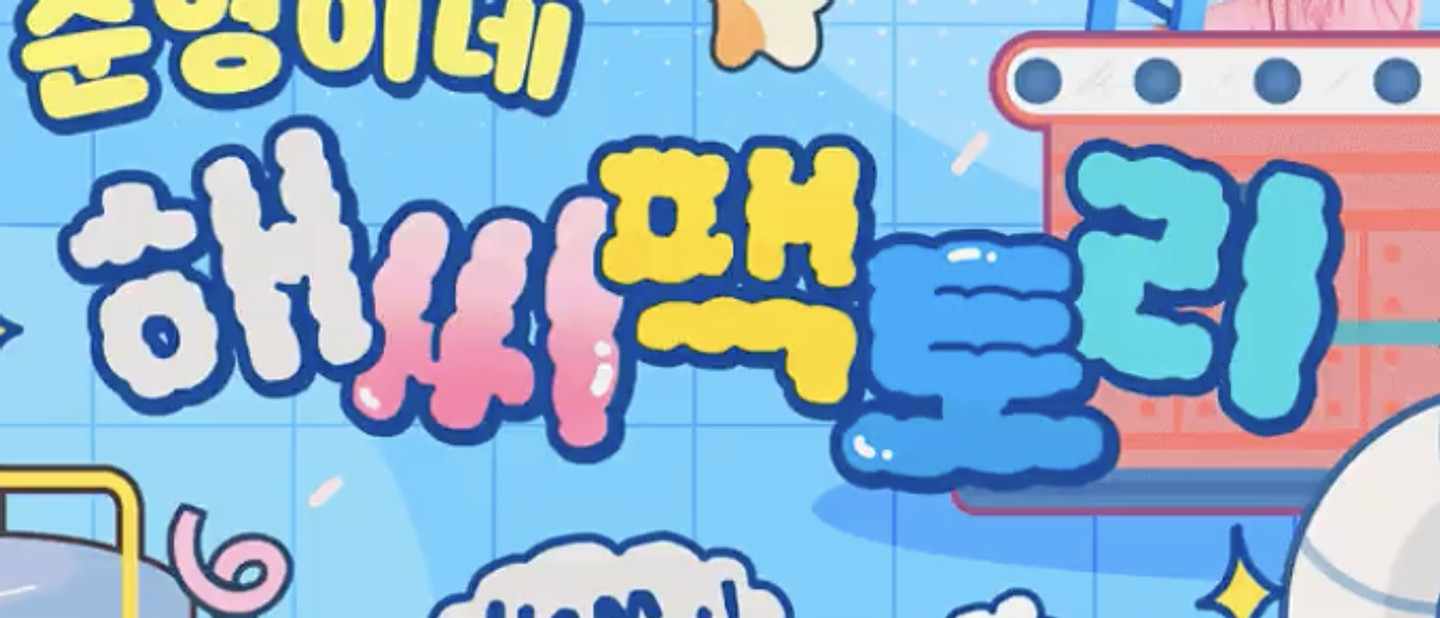
https://twitter.com/kimtaerae_kr/status/1663902547529318401?s=20 위 링크의 PUPPY 랑도 같은 폰트로 보이는데 폰트 정보 부탁드립니다 ㅠㅠ
sandoll 오동통
해당 폰트는 위에 명시드린 폰트에서 별도의 일러스트 프로그램 등에서의 작업을 거쳐 보이는대로 복실복실한 느낌을 따로 디자인한 작업물입니다.